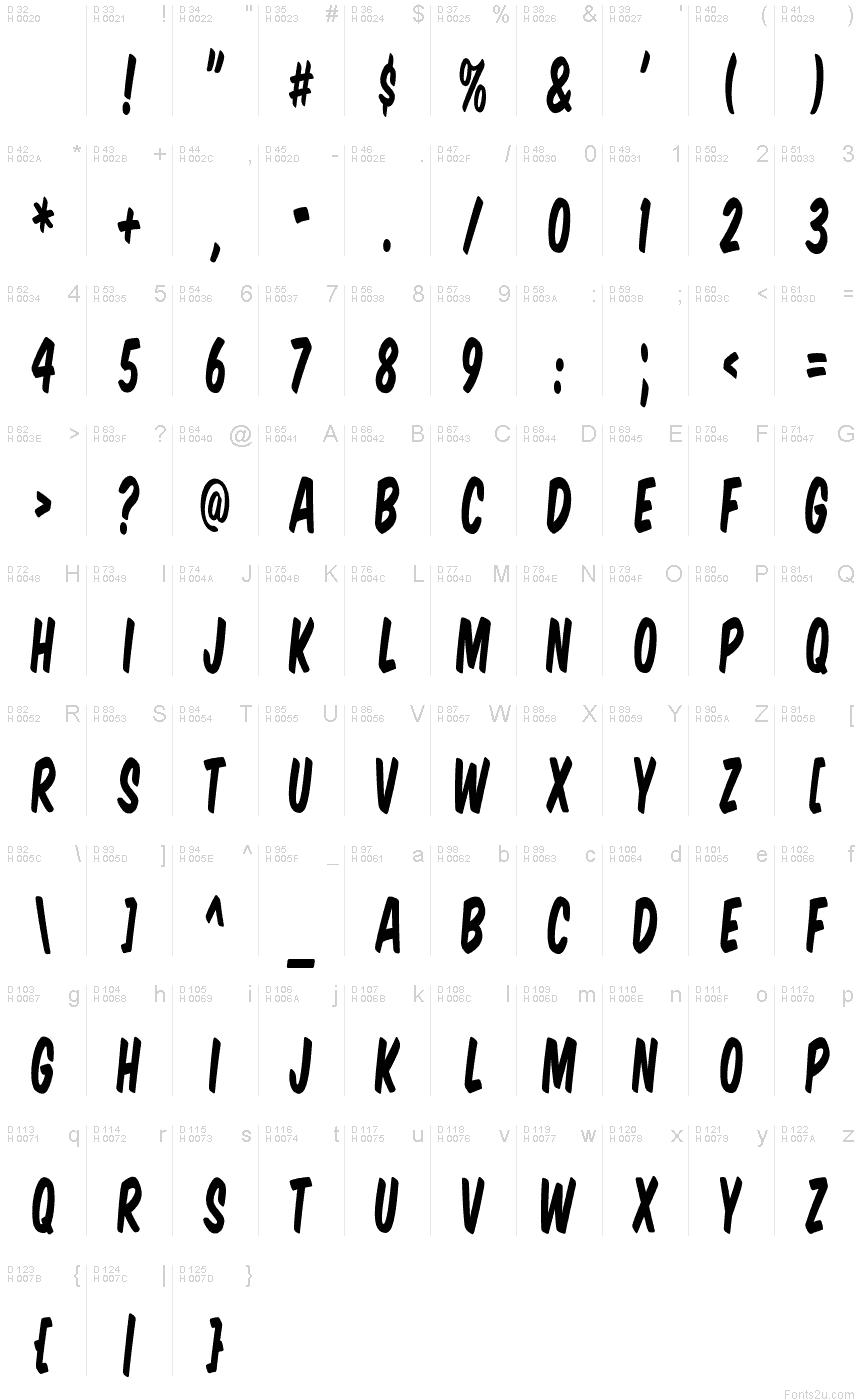
VTC Super Market Sale Tall od VTC Vigilante Typeface Corporation je bezplatné komiksové display písmo se štíhlými, štětcovými tahy, které evokují energii hlasitých supermarketových poutačů. Písmena se naklánějí a kolébají, mají silné, inkoustové tahy, úzké proporce a zaoblené rohy, díky čemuž celé písmo působí rychle, ručně malovaně a trochu divoce.
Hodí se na plakáty, nadpisy letáků, výkladní skříně, pozvánky na večírky a obálky zinů, kde krátká slova potřebují ten správný prodejní říz. Jako bezplatný font funguje také skvěle pro titulky, branding ve stylu nálepek nebo výrazné cenovky, protože vysoká písmena lze těsně poskládat, aniž by ztratila svůj ležérní a křiklavý charakter.